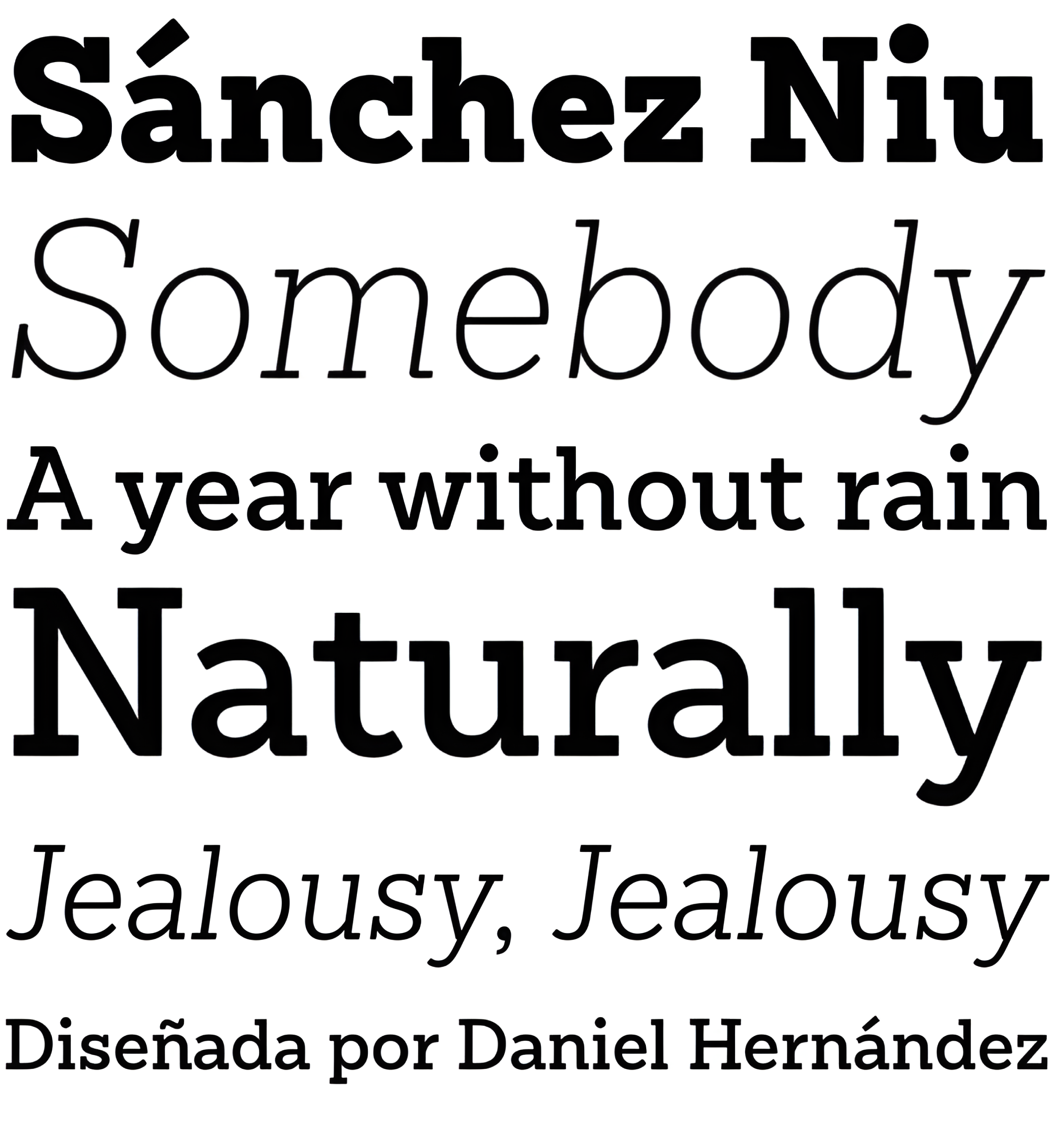
| Créditos | Daniel Hernández |
| Descripción | Sánchez Niu es un rediseño de Sánchez-una de las primeras familias tipográficas de Latinotype diseñada en 2011. En la industria del diseño tipográfico, los términos «nova», «neue», «next», «new» se utilizan a menudo para referirse a un tipo de letra que ha sido modificado de diferentes maneras: rediseño, reajustes técnicos, mayor número de caracteres, etc. En Latinotype estamos empezando a utilizar la palabra «niu» para referirnos a este tipo de tipos de letra. Niu es una adaptación de la palabra original «new», es decir, hemos adaptado esta palabra inglesa a la fonología y ortografía de nuestro propio idioma pero manteniendo el significado original. El mestizaje, la diversidad, el cambio y la adaptación forman parte de la esencia de la cultura latinoamericana y, en Latinotype, todos expresamos constantemente estos elementos en todo lo que hacemos. ¡Poder latino! Esta nueva versión incluye mejoras que la hacen funcionar bien con textos más largos. Sin embargo, estas mejoras no han tenido un efecto importante en el aspecto de la fuente. Hemos ajustado las proporciones originales y añadido una serie de caracteres nuevos, así como características OpenType como versalitas, cifras oldstyle, números tabulares y alternancias estilísticas. Sánchez Niu contiene un conjunto de 720 caracteres compatibles con 219 idiomas. La fuente es adecuada para textos largos, titulares y logotipos, y se ha optimizado para su uso en la web. Sánchez Niu incluye dos fuentes gratuitas: Regular y Regular Italic. Correcciones, edición digital y revisión por César Araya, Rodrigo Fuenzalida y Alfonso García. |